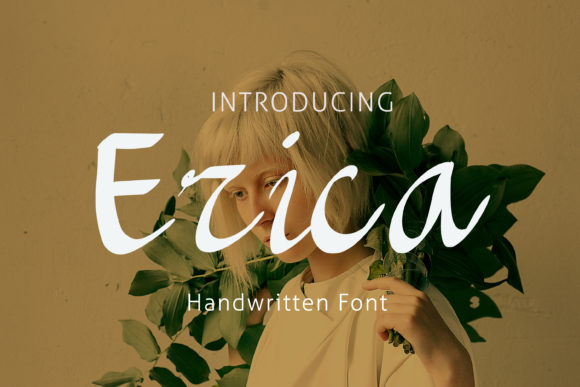
Creativefabrica Erica Font
[Creativefabrica] Erica Font
Эрика - игривый и современный шрифт сценария.
Невероятно выразительный и интересный, этот шрифт оживит каждый из ваших дизайнов. Добавьте его уверенно в свои проекты, и вам понравится результат.